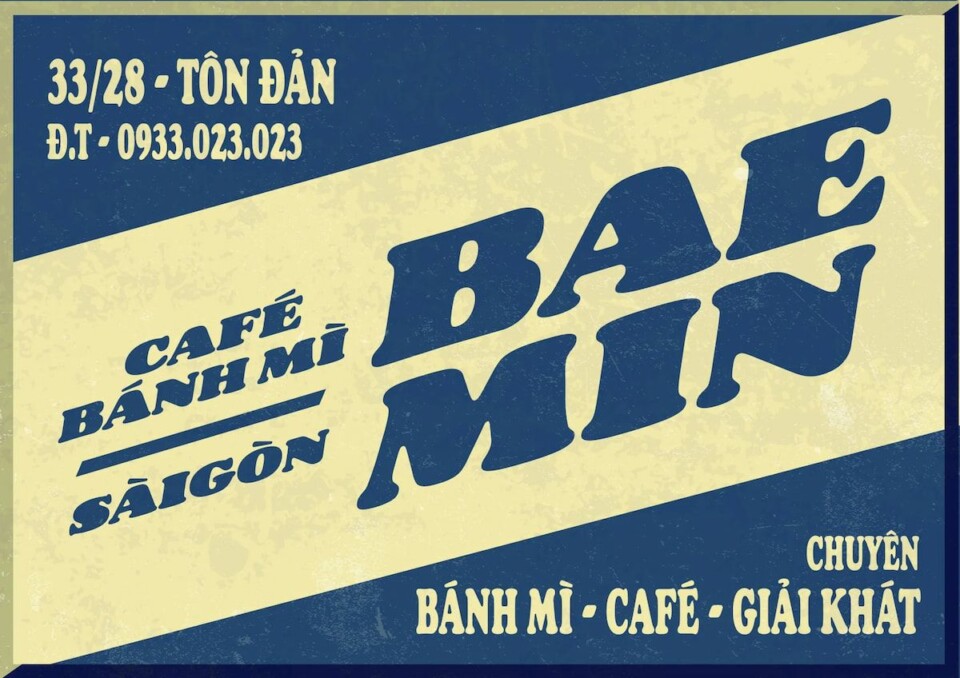
Font BM Lucas Việt hóa – Font mới từ BAEMIN
Font BM Lucas Việt hóa – Font mới từ BAEMIN cho thiết kế sáng tạo
Giới thiệu về Font BM Lucas Việt hóa – Font mới từ BAEMIN
Nếu bạn đang tìm kiếm một làn gió mới cho các bản thiết kế học đường hoặc dự án cá nhân thì Font BM Lucas Việt hóa – Font mới từ BAEMIN chính là lựa chọn không thể bỏ qua. Đây là bộ Font Miễn Phí mang đậm phong cách trẻ trung, hiện đại và vô cùng gần gũi. Được phát triển dựa trên bản sắc thương hiệu độc đáo của ứng dụng giao đồ ăn nổi tiếng, bộ font này giúp truyền tải thông điệp một cách hóm hỉnh và sinh động hơn bao giờ hết.
Đặc điểm nổi bật của Font BM Lucas Việt hóa
Thiết kế tối ưu cho tiếng Việt
Điểm mạnh nhất của Font BM Lucas Việt hóa – Font mới từ BAEMIN chính là việc xử lý các dấu thanh cực kỳ chuẩn xác. Các bạn học sinh và thầy cô có thể yên tâm sử dụng trong các bài thuyết trình hay thiết kế báo tường mà không lo lỗi hiển thị. Với các đường nét bo tròn mềm mại nhưng vẫn giữ được sự ngay ngắn, font chữ này tạo cảm giác dễ đọc và rất thiện cảm đối với người xem.
Ứng dụng đa dạng trong học tập và đời sống
Nhờ tính linh hoạt cao, bộ font này thường được ưu tiên sử dụng cho các tiêu đề video, thiết kế bìa sách hoặc các poster sự kiện tại trường học. Phong cách thiết kế của BAEMIN vốn nổi tiếng với sự tối giản nhưng đầy tính biểu cảm, giúp các bạn trẻ dễ dàng định hình phong cách riêng trong từng tác phẩm đồ họa.
Kết luận về bộ font mới từ BAEMIN